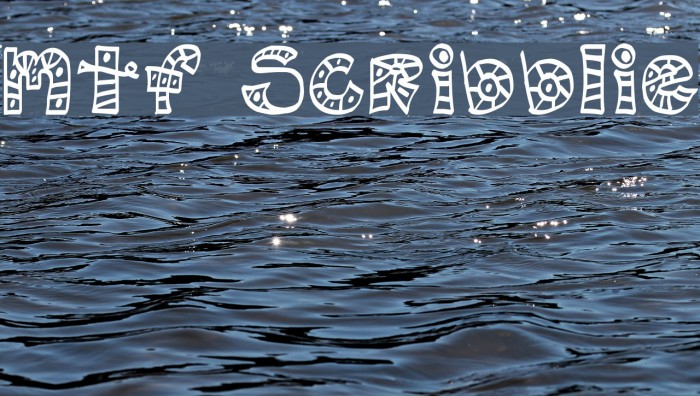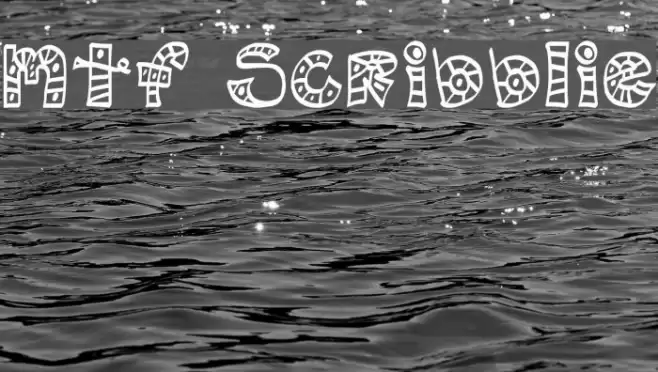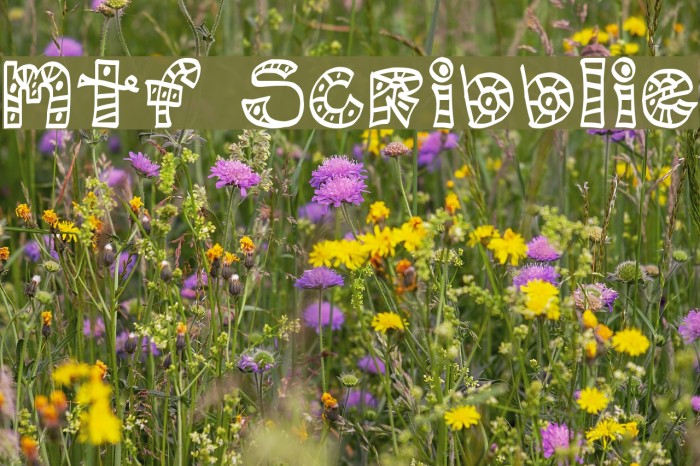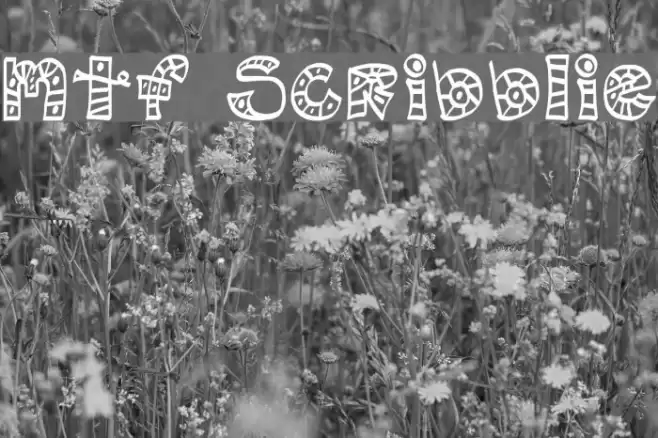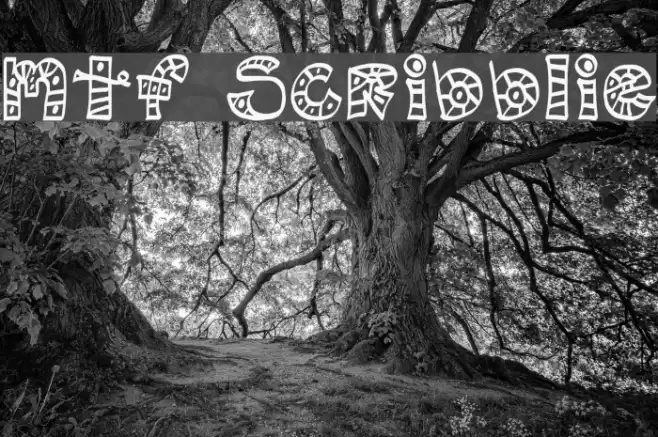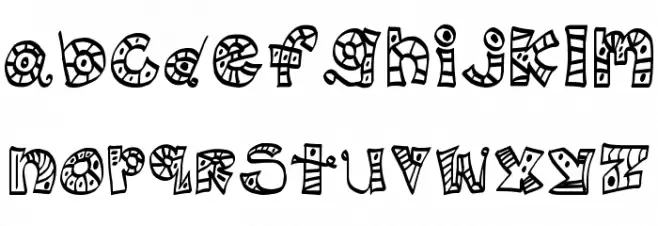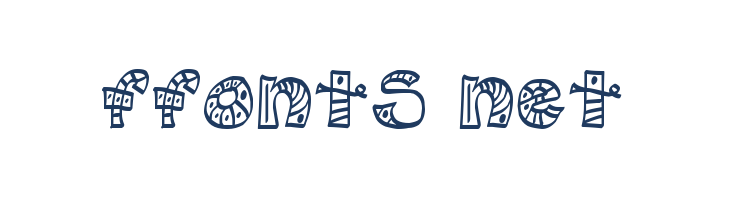
MTF Scribblie Font
✎ Comic
| Gesamtstil | Whimsical, Artistic, Fun |
| Anwendungsfall | Headlines, Posters, Creative Projects |
| Vorgeschlagene Projekte | Ideal for children's book covers, playful invitations, creative posters, and artistic branding. |